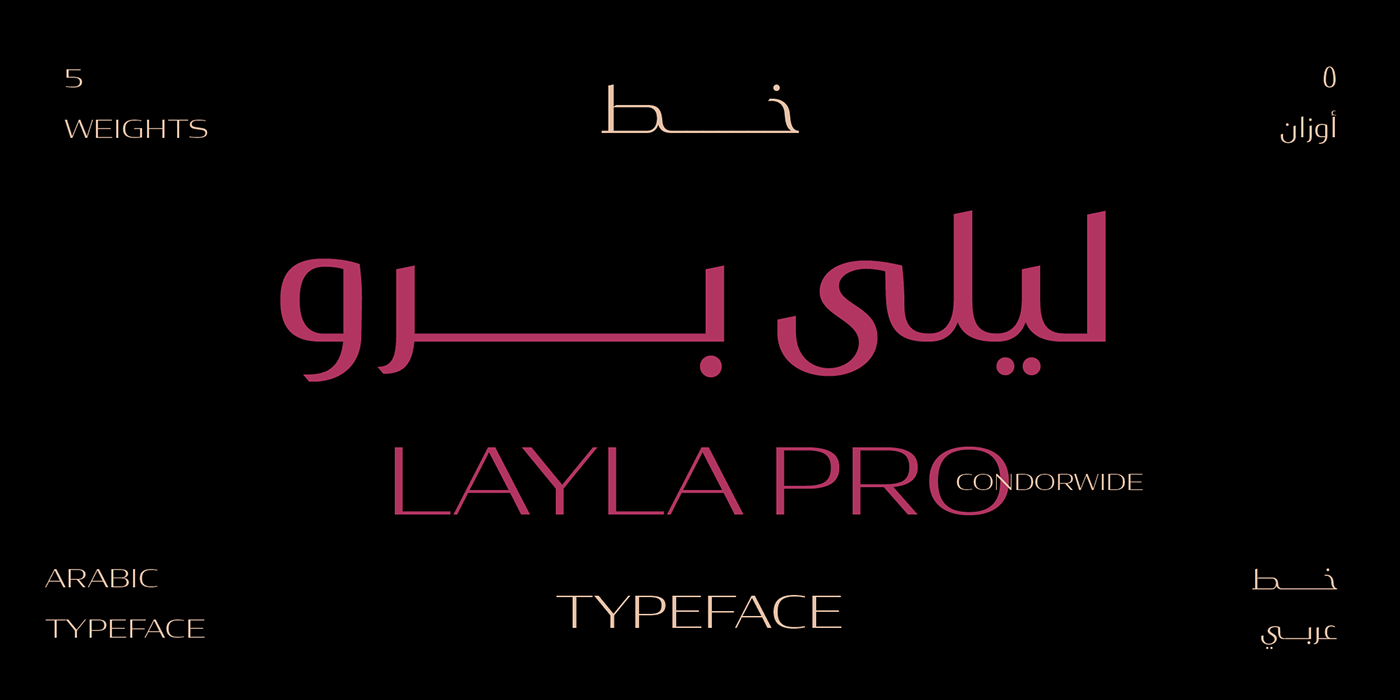
دانلود فونت فارسی لیلا – Layla arabic
تایپ فیس عربی لیلا یک حروف عربی مدرن است که توسط احمد زازا طراحی شده است. این طرح الهام گرفته از سبک خط کوفی و متاثر از سبک نسخ است. نتیجه ترکیبی است که تناسبات مدرن را با خطهای عربی کلاسیک ترکیب میکند.